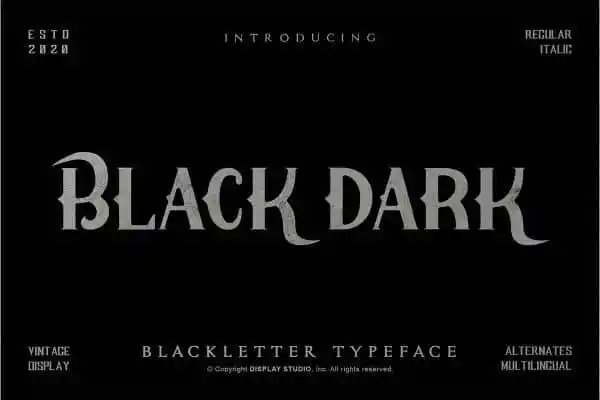
Introduzimos a Black Dark Display Font, uma tipografia para exibição feita para ambas as épocas atuais e passadas. Especialmente projetada pela Display Studio, esta fonte inclui letras maiúsculas, números e alguns sinais de pontuação. Com traços e contraste invertido, ela se destaca perfeitamente como uma tipografia para exibição, ideal para headlines ou qualquer tipo de texto que deseje destacar e criar um impacto visual a primeira vista. Além disso, é uma fonte versátil que pode ser usada tanto para títulos quanto para textos. Seja você um designer gráfico buscando um recurso atraente para seus projetos, ou simplesmente alguém procurando um upgrade em suas ferramentas de design, a Black Dark Display Font certamente terá uma solução perfeita.